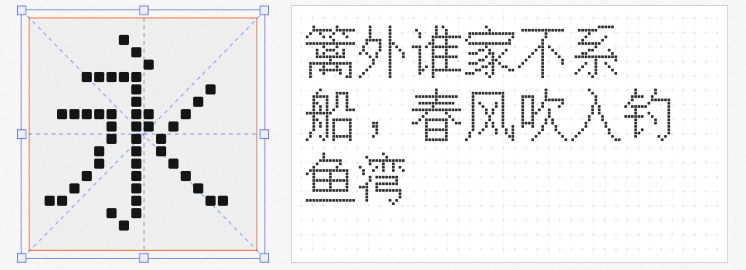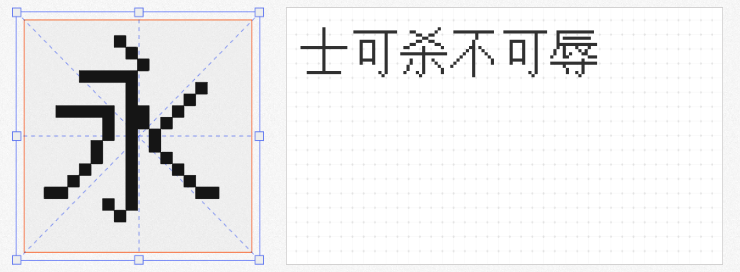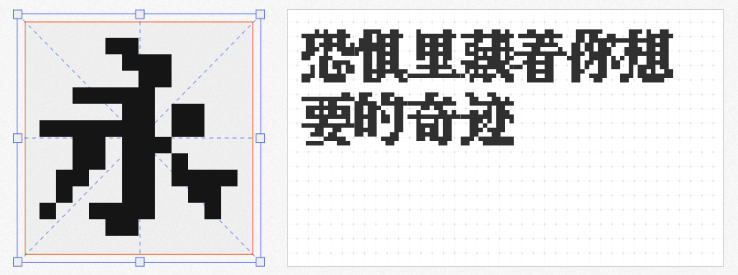
四款免费商用像素字体推荐:复古、科技与极简的视觉碰撞
在像素艺术与低多边形设计复兴的当下,像素字体凭借其独特的复古质感和数字时代的科技感,成为游戏、UI界面、品牌视觉等领域的设计利器。本文精选四款免费商用的优质像素字体,涵盖不同风格与应用场景,助力设计师高效打造视觉亮点。
1. 长坂点宋
「长坂点宋」以经典日式点阵字体「KHドット道玄坂12」为蓝本,通过补足简体字与繁体字库,打造出12px的粗宋体像素字体。其笔画粗细对比强烈,转折处保留机械感的锯齿细节,完美复刻街机游戏与老式招牌的视觉氛围。适用于复古风格游戏标题、霓虹灯牌设计或赛博朋克主题海报,为作品注入怀旧未来主义气质。
2. 甜橙点阵体
作为7像素点阵字体中的佼佼者,「甜橙点阵体」通过优化字重分布与笔画间距,解决了小尺寸像素字体的模糊难题。由ZFONT团队修正字高与ROS信息后,字体支持简体中文全字符集,且在极低分辨率下仍能保持清晰可读性。推荐用于游戏界面数值显示、软件工具栏标签或智能穿戴设备UI,以极简像素传递高效信息。
3. 纳米点宋
由独立设计师寒沙打造的「纳米点宋」,突破传统点阵字体依赖Unifont的局限,采用定制Mono字形结构。其等宽特性与均匀的像素分布,使其成为代码编辑器、终端界面的理想选择,同时兼顾中文与西文的视觉平衡。无论是深色主题的IDE界面,还是数据可视化仪表盘,纳米点宋都能以冷静的理性美感提升专业质感。
4. 金字社统方体
作为Unifont的衍生字体,「金字社统方体」严格遵循JY-MCU 6cm×6cm点阵显示屏的物理规格,每个字符均由6×6像素矩阵构成。这种极致规整的像素排列,使其成为硬件原型设计、物联网设备界面或嵌入式系统开发的完美配套字体。设计师可借助其机械美感,打造科技感十足的工业产品视觉系统。
从长坂点宋的复古情怀到纳米点宋的编程理性,这四款字体以像素为画笔,勾勒出数字时代的设计多样性。所有字体均支持免费商用,设计师可放心将其融入商业项目,为作品注入独特的像素美学。